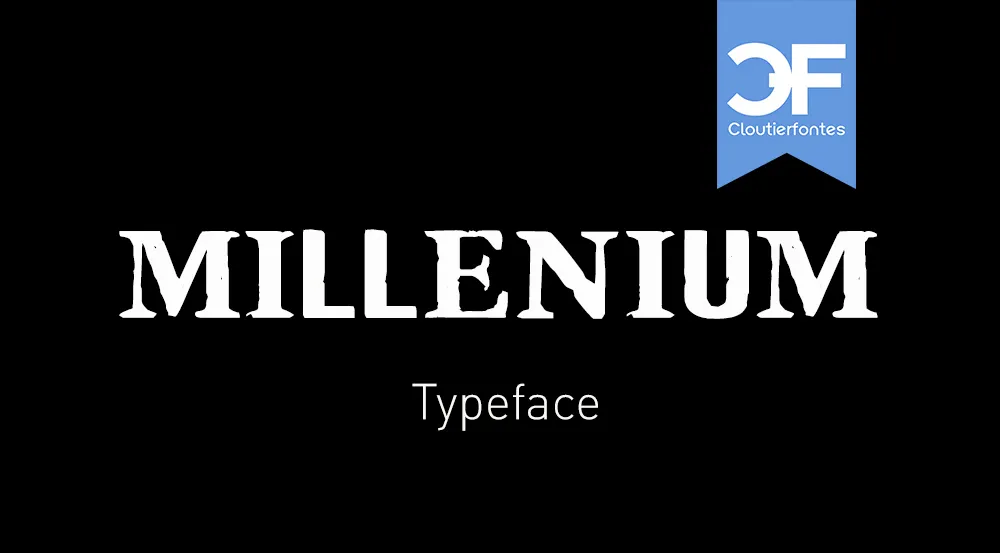
CF Millenium Font – Download Grátis
A CF Millenium é uma fonte que foi meticulosamente criada para oferecer precisão e detalhes cuidadosos, tornando-a ideal para múltiplas aplicações visuais. Seu design clean e moderno permite que seja usada com perfeição em variadas tarefas gráficas como quoterias, headlines, logotipos, rótulos, grafismos e embalagens. Com uma aparência de alta qualidade, a CF Millenium proporciona um contraste elegante e distintivo, tornando-a uma opção preferencial para quem busca estética moderna em projetos de design visual. Seja você criador de materiais digitais ou impressos, certamente encontrará na CF Millenium Font o recurso perfeito para destacar seu trabalho gráfico com estilo e eficácia.